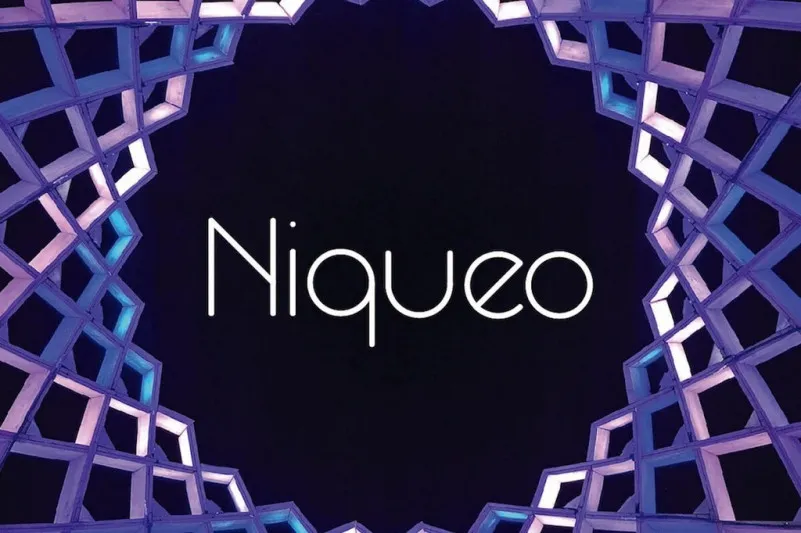
Niqueo é uma elegante fóntes sans-serif monoline que foi criada pelo talentoso designer Nico Rodriguez. Este tipo de texto não apresenta traços nos cantos, proporcionando um aspecto clean e moderno. A Niqueo oferece suporte a múltiplas línguas, o que a torna versátil para uso em diversos formatos de mídia. Esse fonte inclui letras maiúsculas e minúsculas, números e símbolos, garantindo uma extensibilidade completa. A Niqueo é perfeita para headlines, documentos, revistas, títulos, roupas, posteres e muito mais. Seja você um designer gráfico ou editor de texto, a Niqueo irá transformar seu trabalho em algo especial. Não perca tempo, baixe a fonte Niqueo agora!